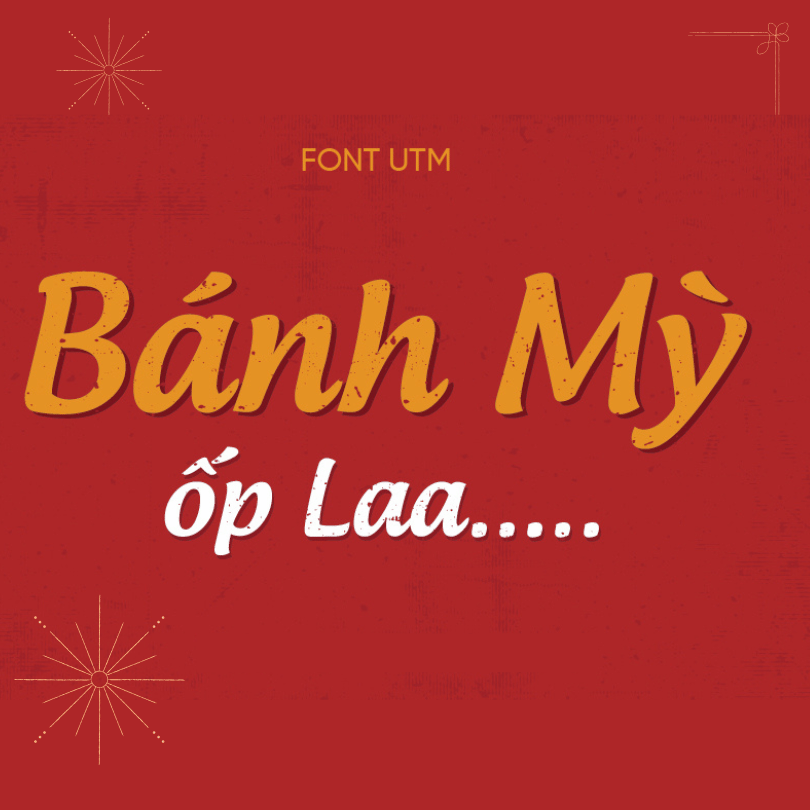
Font UTM Androgyne là một trong những kiểu chữ được ưa chuộng trong thiết kế đồ họa và in ấn tại Việt Nam. Được phát triển bởi Công ty TNHH UTM, font này mang lại sự hòa quyện giữa tính hiện đại và truyền thống, làm cho nó trở thành lựa chọn lý tưởng cho nhiều dự án.
Với thiết kế thanh thoát, UTM Androgyne có độ dày chữ vừa phải, giúp tăng tính dễ đọc cho người dùng. Các ký tự được thiết kế tỉ mỉ với các đường nét mềm mại, mang đến cảm giác nhẹ nhàng và dễ chịu cho người nhìn. Font này phù hợp với nhiều thể loại văn bản, từ tiêu đề cho đến nội dung chính, giúp tạo ra sự nhất quán trong các tài liệu.
Một điểm đặc biệt của UTM Androgyne là khả năng hỗ trợ tốt cho tiếng Việt với đầy đủ các dấu câu và ký tự đặc trưng. Sự đa dạng trong kích thước chữ cũng như phong cách thiết kế giúp nó có thể linh hoạt sử dụng trong nhiều ngữ cảnh khác nhau, từ biển quảng cáo, tờ rơi cho đến các sản phẩm truyền thông trực tuyến.
Ngoài ra, UTM Androgyne còn có thể kết hợp hài hòa với nhiều kiểu chữ khác để tạo ra những thiết kế độc đáo và ấn tượng. Với những ưu điểm nổi bật về mặt thẩm mỹ và chức năng, UTM Androgyne thực sự là một lựa chọn tuyệt vời cho các nhà thiết kế và doanh nghiệp.